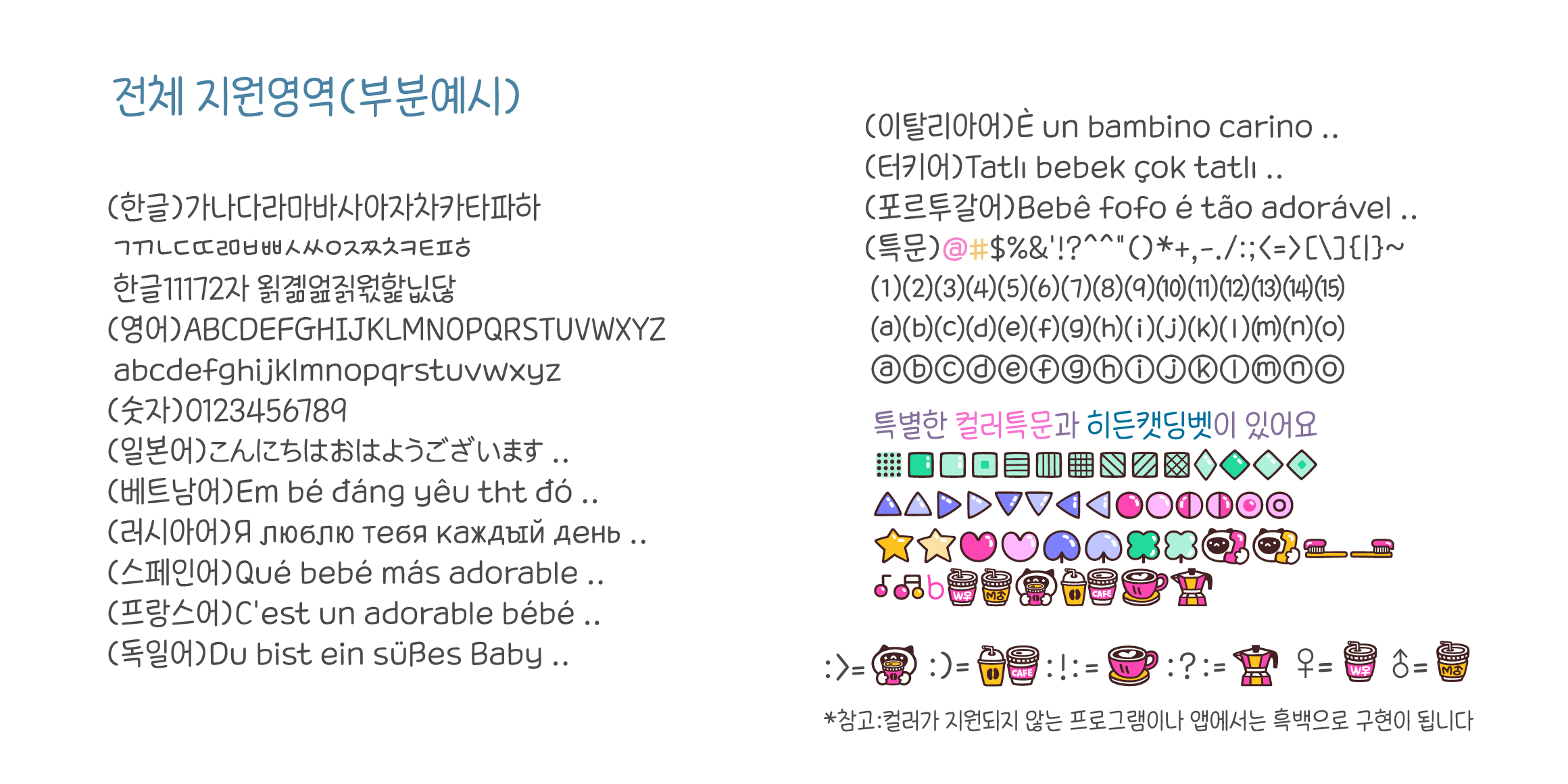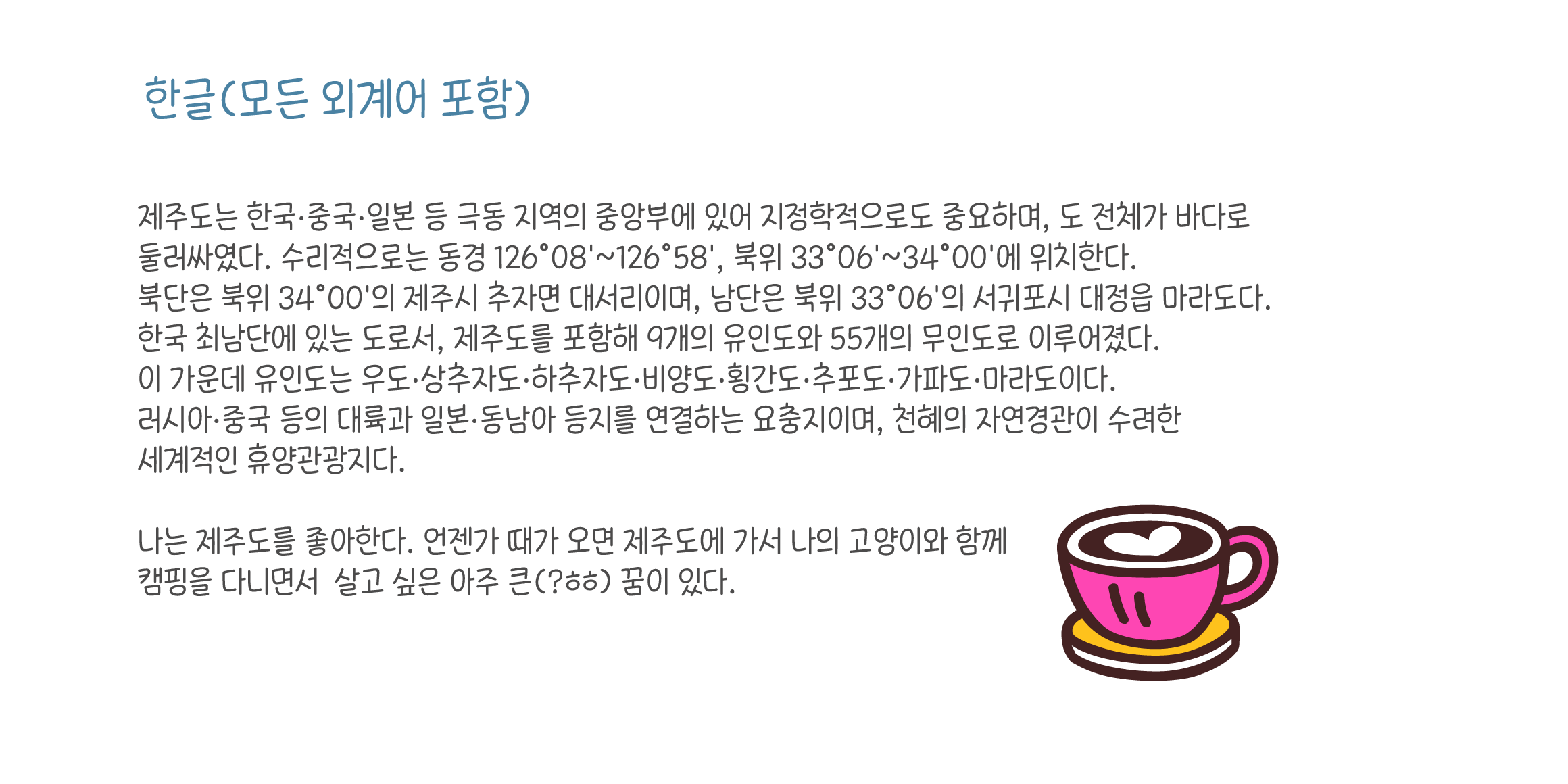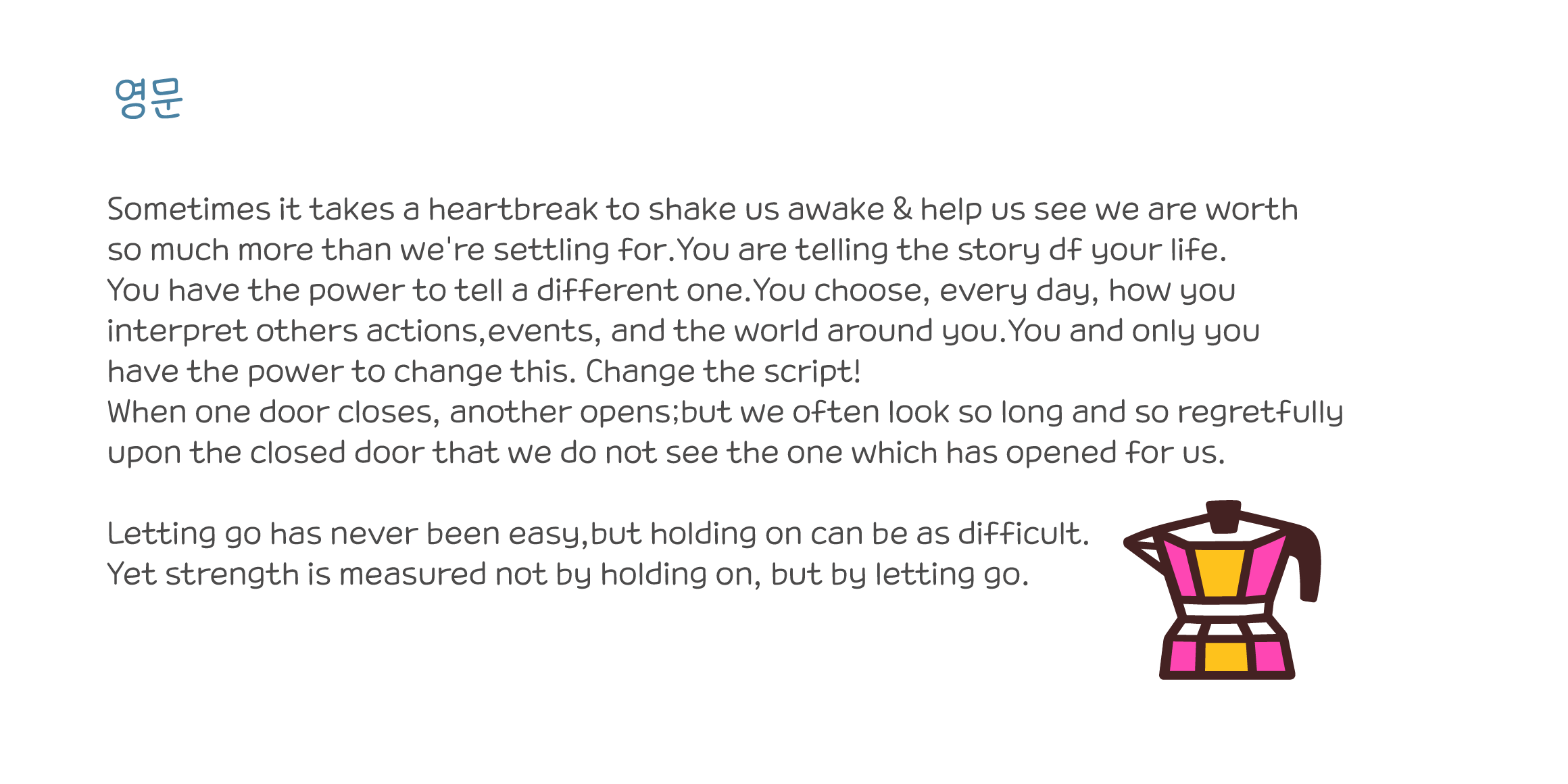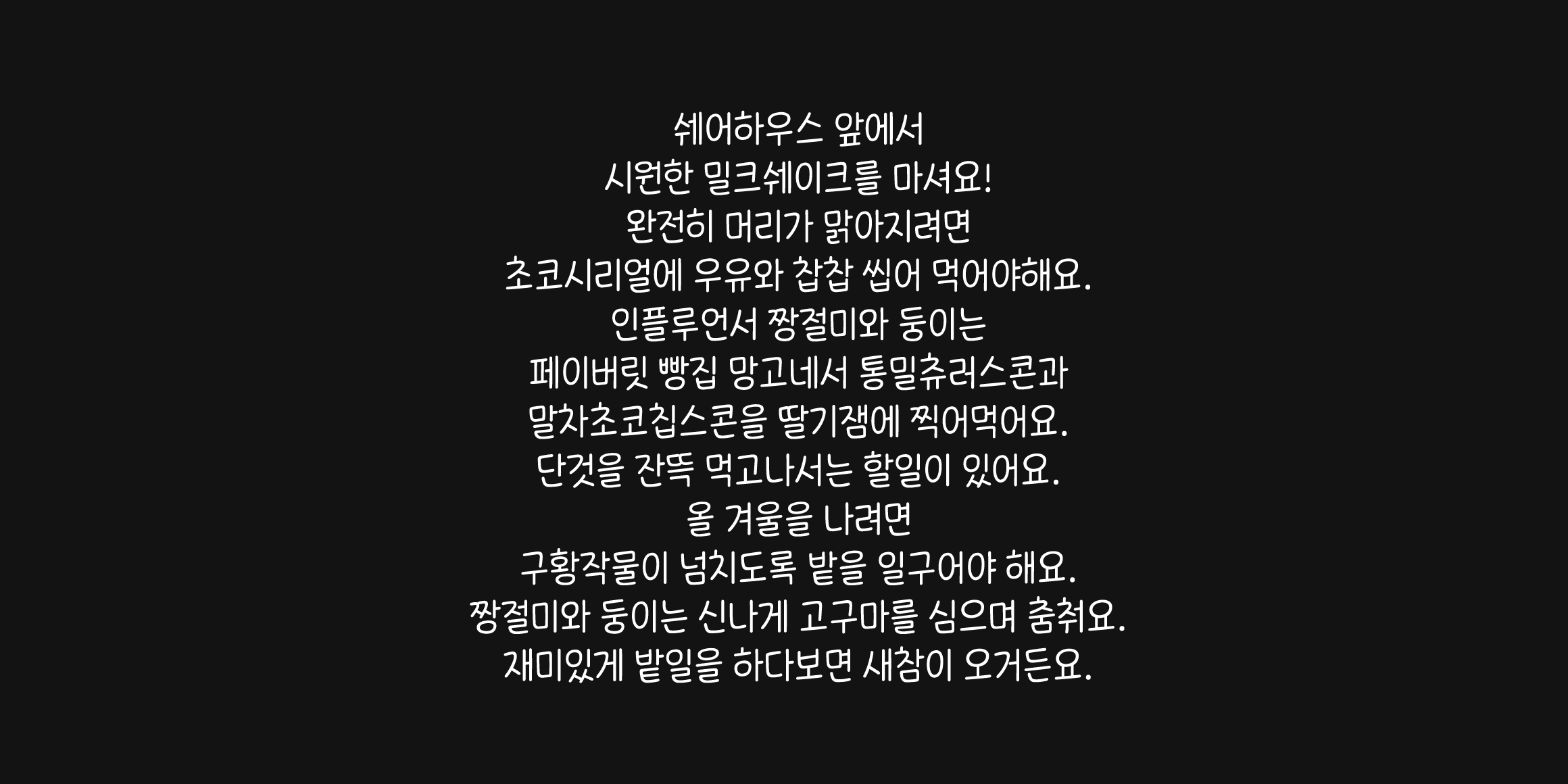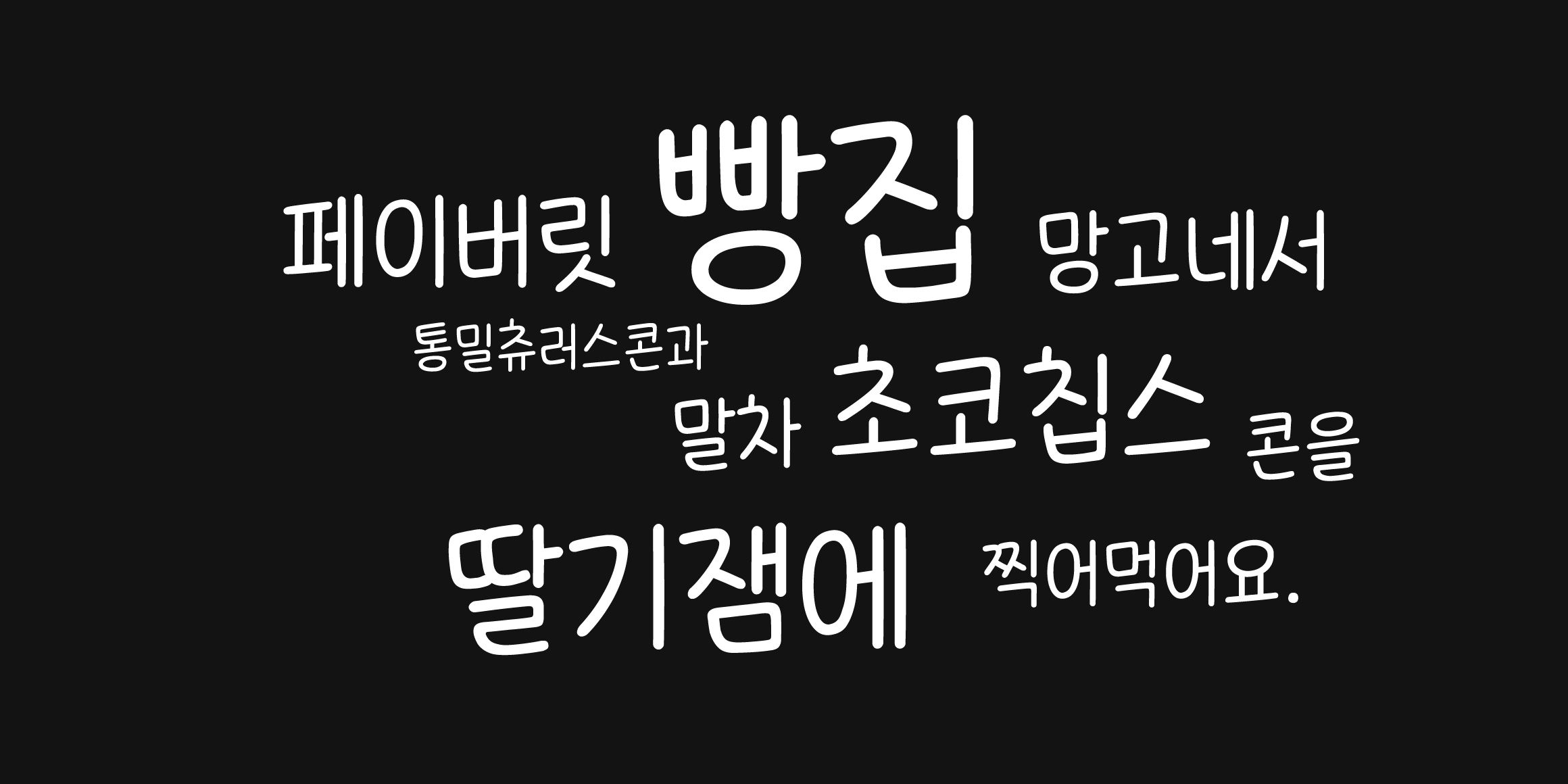
취향에 맞는 커피를 마실 때의 기분좋음을 표현한 글꼴입니다.
밝고 경쾌하고 군더더기 없는 깔끔한 느낌이며
가독성이 좋아 보기에 편합니다.
♥키보드 ; > ; ) : ! : : ? : 을 연달아 치면
매력적인 캣딩벳이 나타납니다.
♥영어 일어 베트남어를 포함한
독일 프랑스 러시아 이탈리아 포르투갈 스페인 터키 등
유럽의 다양한 국가들의 언어도 함께 지원하는 등
폭넓은 언어와 특수문자 지원을 합니다.
♥캣폰트의 디자인은 오랜 시간 연구한 결과물입니다.
*컬러가 지원되지 않는 단말기나 앱이 있을 수 있습니다.
*컬러가 들어간 글자들은 두껍게(Bold)처리를 해도 두께 변화가 없습니다.
- Cat2한잔의커피 / Cat2Acoffee